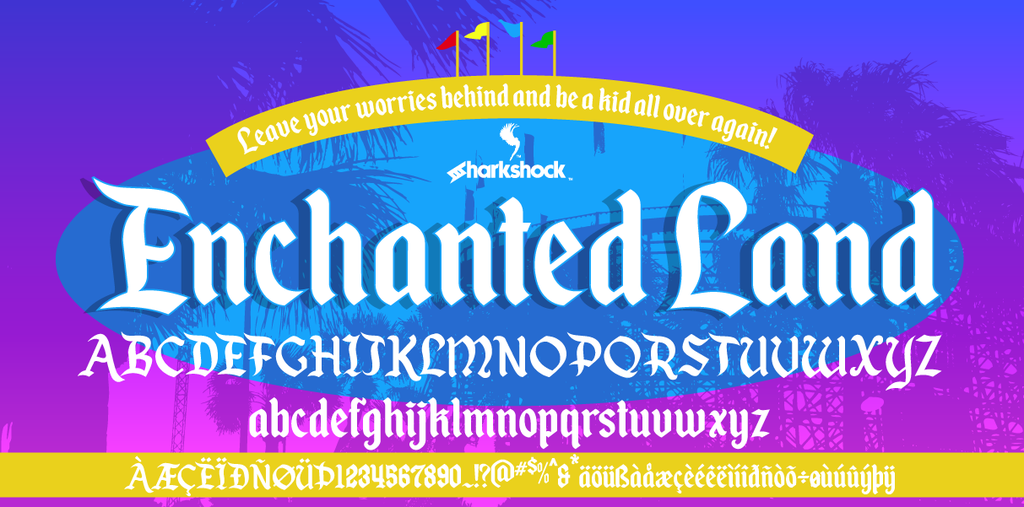
Na categoria de Fonts Góticas, a ‘Enchanted Land Font’ é um projeto fascinante criado pelo designer Hamilton. Essa fonte oferece uma atmosfera envolvente e natural que certamente tornará sua próxima criação digital impecável. Inspirada por Dennis Ludlow em 2016, essa fonte vem com todos os direitos reservados pelo Sharkshock. Se você está procurando por um recurso gráfico que transmita beleza e profundidade de maneira única, esta é uma ótima opção. Com seu design gótico contemporâneo, a ‘Enchanted Land Font’ será o toque final para qualquer projeto de criação digital. Além disso, os formatos OTF e TTF tornam essa fonte ainda mais versátil e acessível para todos os seus projetos digitais. Não perca esta oportunidade de adicionar uma nova dimensão ao seu trabalho com a ‘Enchanted Land Font’.